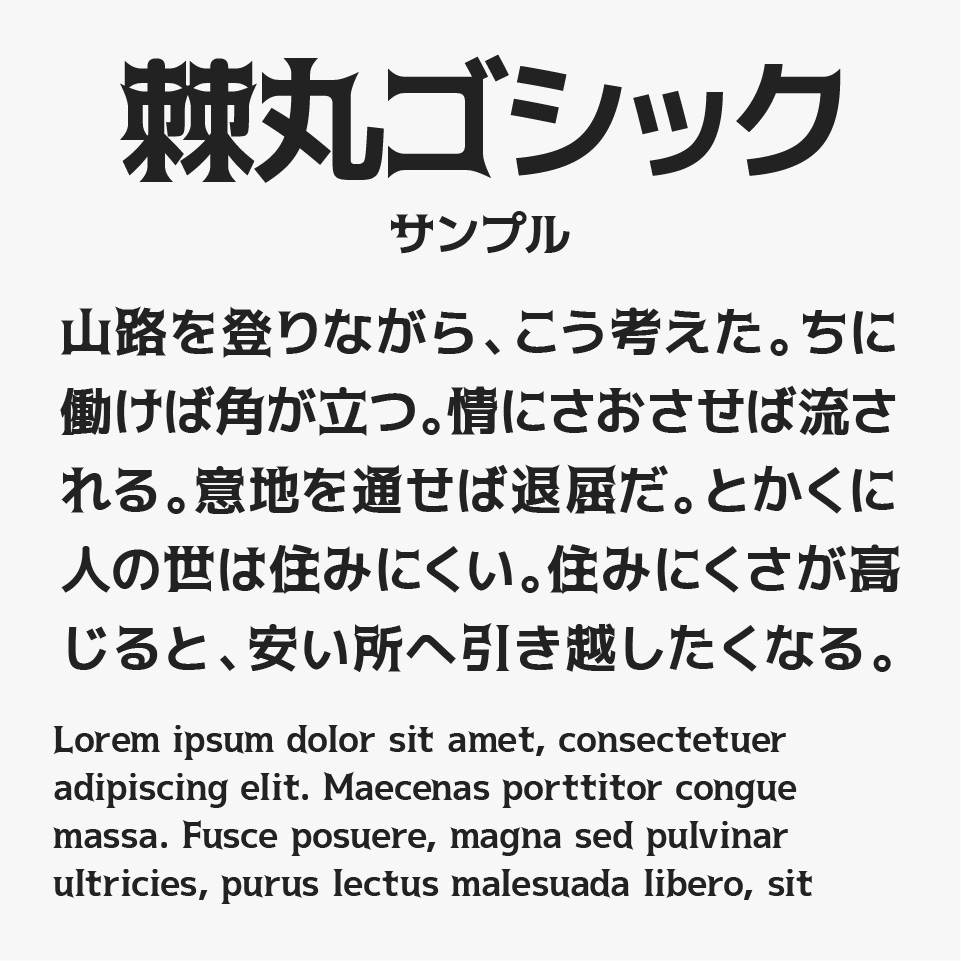
棘丸ゴシック
棘丸ゴシックフォントは、ゴシック体の文字をベースに、文字先端にトゲのような装飾と、丸のモチーフが組み合わせって作られたデザインフォントです。
トゲトゲした印象が、カッコいい印象があるフォントなので、タイトルなどに取り入れてみると良さそうです。また動画編集者にも人気あるフォントなので、テロップやサムネイルのタイトル文字などに利用されていることも多いフォントです。
フォントウエイトは、ExLight・Light・Regular・Medium・SemiBold・Bold・Heavyの7種類が用意されています。